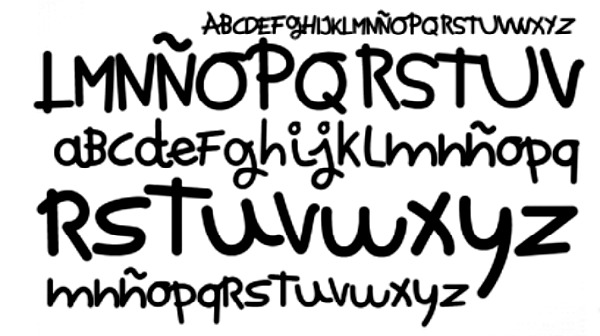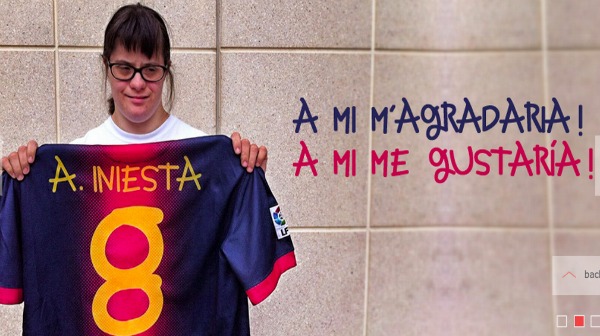
Anna, la letra de una chica con síndrome de Down que se convirtió en tipografía
Anna Vives no pasaba por su mejor momento. “No tenía trabajo. Estaba en casa sin hacer nada, triste”. Preocupados por ella, sus familiares, entre ellos su hermano Marc, sabían que lo que Anna necesitaba era ocupar su mente y su tiempo en algo que la entusiasmara. Y así comenzó a escribir y a dibujar.
“Vino a trabajar a la Fundación Itinerarium, en la que trabajo como director de proyectos. Y allí nos dimos cuenta de que su letra era preciosa”. Y sobre todo muy particular. Porque a esta chica de 27 años y con síndrome de Down le gusta mezclar indistintamente caracteres con mayúscula y minúscula.
Por eso, cuando su hermano y el resto de miembros de la fundación decidieron digitalizarla, tenían muy claro que había que respetar sus trazos al 100%. El proceso ha durado un año y ha sido llevado a cabo por Julen Iztueta, diseñador de la Fundación Itinerarium, quien ha trabajado codo a codo con Anna.
Ahora Anna no está triste. Se siente orgullosa de su trabajo (sobre todo, de cómo ha quedado la letra ‘T’, según su hermano, “su favorita, porque es la letra de ‘Trabajo’). Y también de que más de 25.000 personas en todo el mundo ya se hayan descargado su tipografía. “Centenares de escuelas, instituciones públicas, privadas, marcas, ya utilizan su letra en vez de la Courier o la Comic Sans para documentos informales”.
Incluso instituciones como el FC Barcelona han mostrado interés por la tipografía Anna, según el propio Marc. “El club, a través de su Fundación, ya nos ha comunicado que la utilizará en diferentes acciones a partir de ahora”. Incluso, asegura, que a los jugadores y directivos les gusta la idea de portarla en la equipación oficial, aunque, claro, la última palabra la tiene Nike…